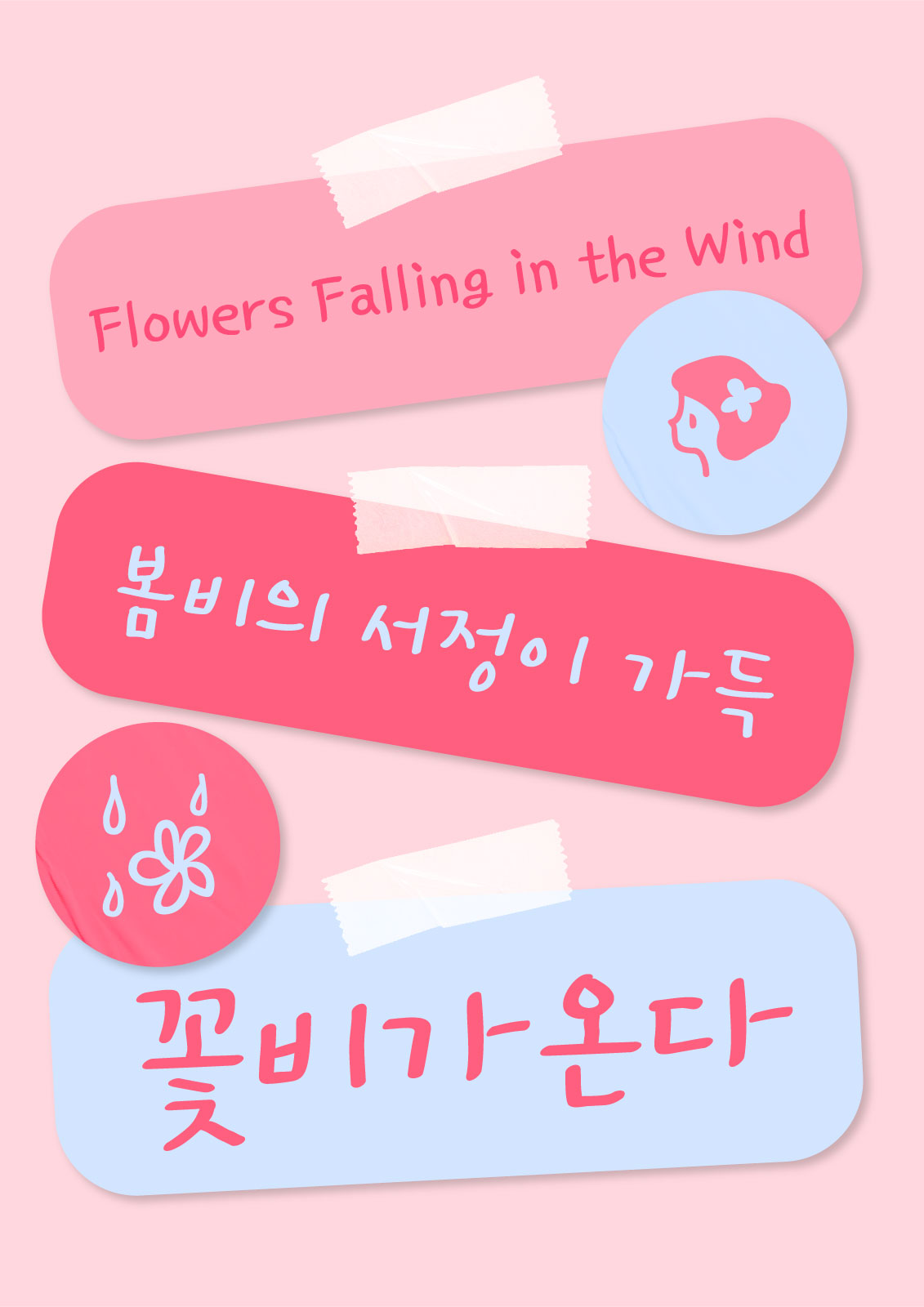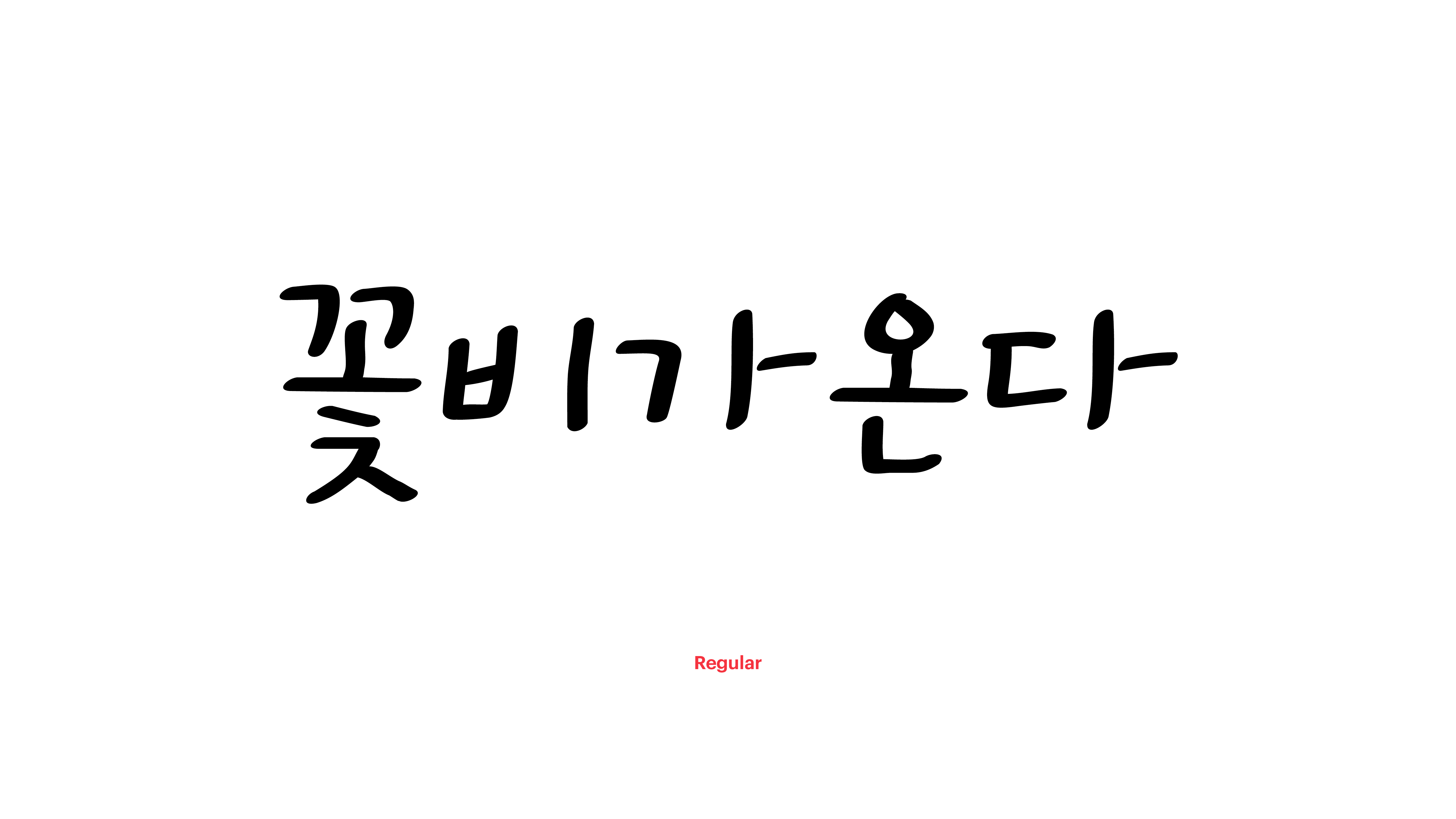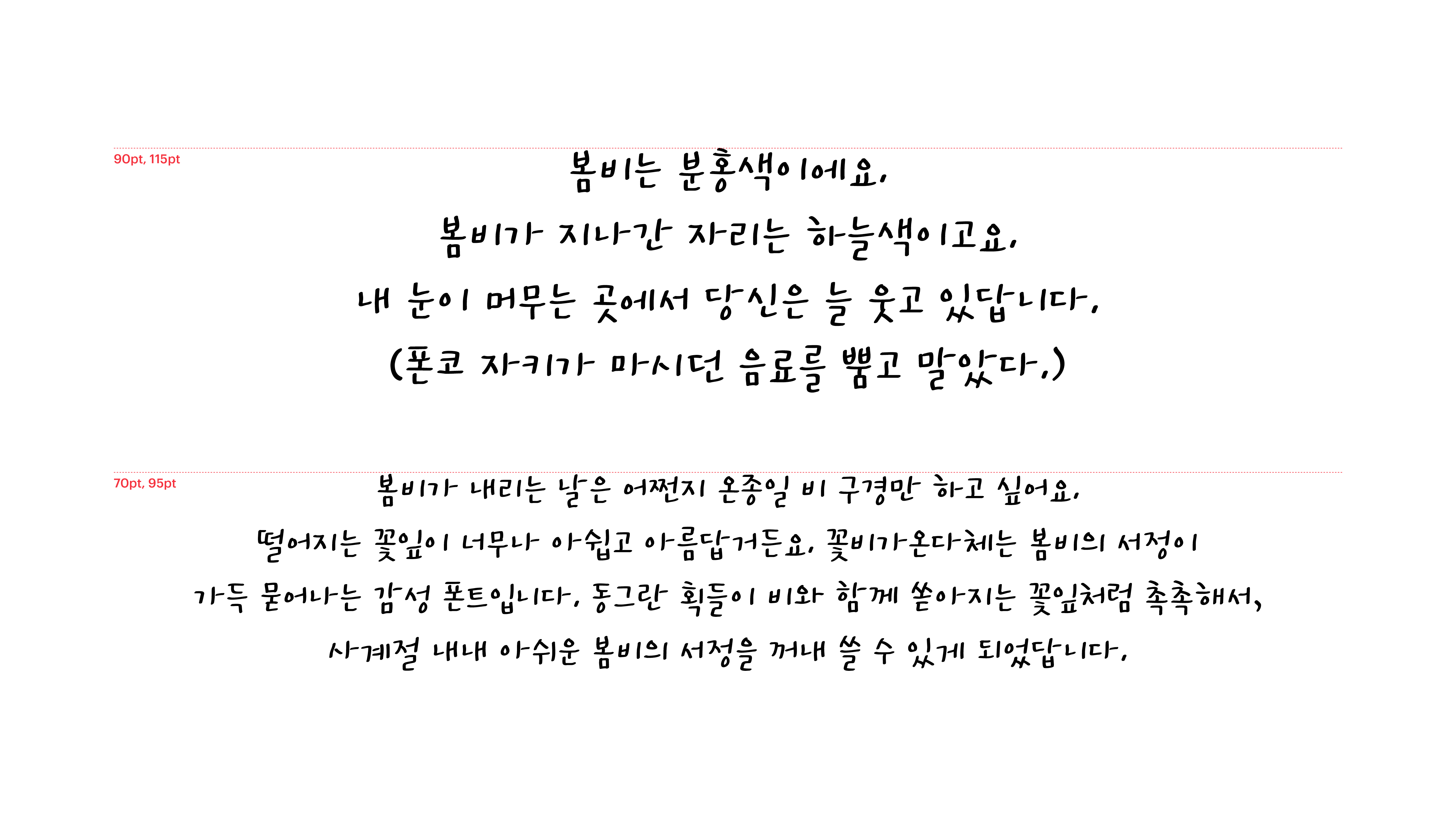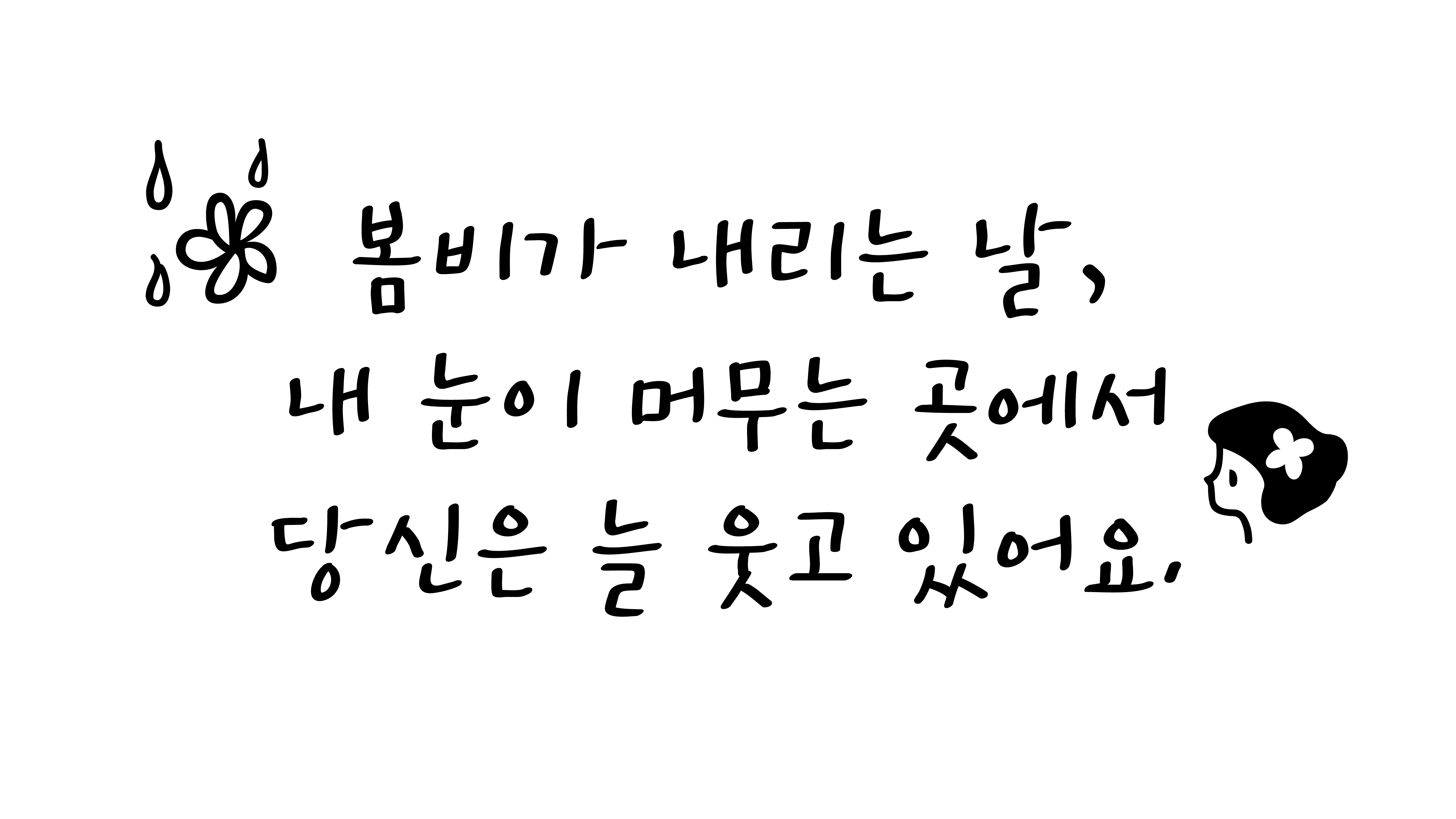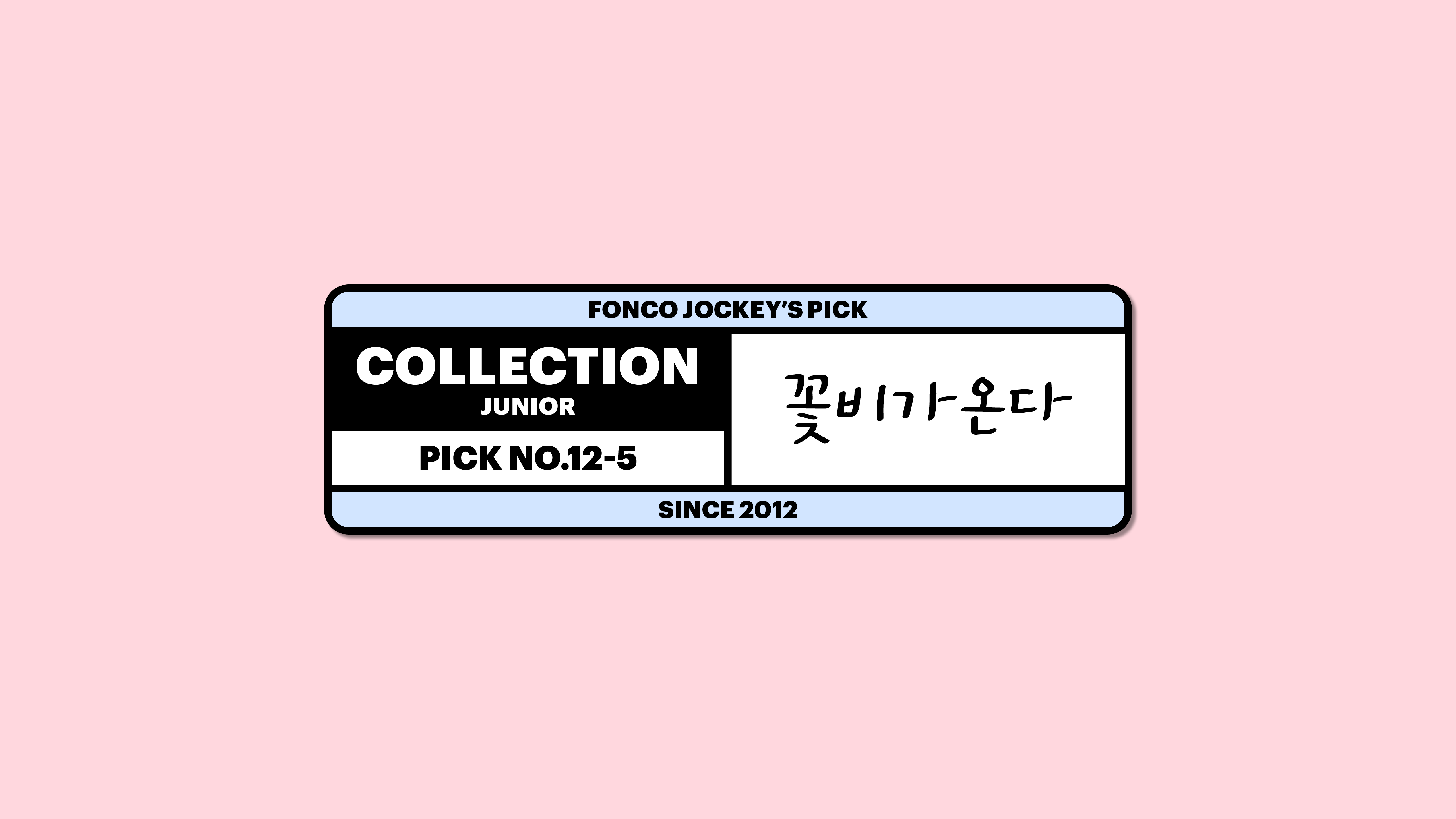
꽃비가온다
Yoon 꽃비가온다
봄비가 내리는 날은 어쩐지 온종일 비 구경만 하고 싶어요. 떨어지는 꽃잎이 너무나 아쉽고 아름답거든요. 꽃비가온다체는 봄비의 서정이 가득 묻어나는 감성 폰트입니다. 동그란 획들이 비와 함께 쏟아지는 꽃잎처럼 촉촉해서, 사계절 내내 아쉬운 봄비의 서정을 꺼내 쓸 수 있게 되었답니다.